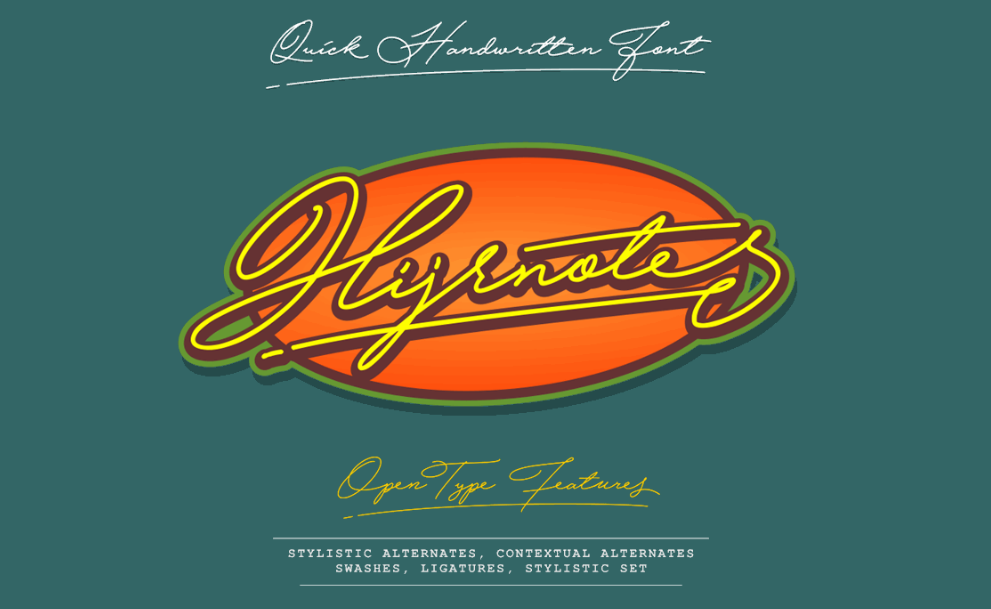
Hijrnotes Font – Fonte Grátis
Hijrnotes Font
A fonte ‘Hijrnotes Font’ é uma cópia cuidadosamente feita de digitais manuscritas, ideal para textos que precisam de um toque personalizado e autêntico. Seja ela usada no design editorial ou em trabalhos profissionais, a fonte oferece uma variedade de opções para destacar sua identidade visual. Neste caso, o designer Hamilton criou uma cópia meticulosa da famosa font ‘Hijrnotes’, que é amplamente utilizada nas páginas de versão escrita do Corão. Esta font tem um estilo elegante e legível, perfeitamente adequado para se destacar em qualquer projeto. Suas linhas delicadas e nuances sutis fazem dela uma escolha segura para designers querendo transmitir tranquilidade e confiabilidade através da sua tipografia. Para quem está procurando por um recurso gráfico que pode ajudá-lo a destacar sua identidade ou produzir trabalhos profissionais, a ‘Hijrnotes Font’ é uma opção atraente. Seu designer Hamilton nos dá a oportunidade de acessar uma font cuidadosamente copiada e adaptada, mantendo a essência autêntica da original. Visite o site [Mansgreback](http://www.mansgreback.com/hijrnotes) para mais informações sobre licenciamento comercial.